不同的字体有不同的风格,毛笔书法作为中国悠久的经典艺术,注重规章制度和布局,也是作者情绪的外在反映,毛笔书法的朝代变迁也形成了多家字体的百花齐放。今天分享几款,喜欢的朋友可前往字体视界下载。
汉标老梁行楷书法气息浓厚,结字潇洒俊逸,运笔行云流水,气韵生动,充分体现新毛笔行书味道。适用于文艺类的书刊、品牌广告和产品包装设计,以及社交网络的个性化用字。
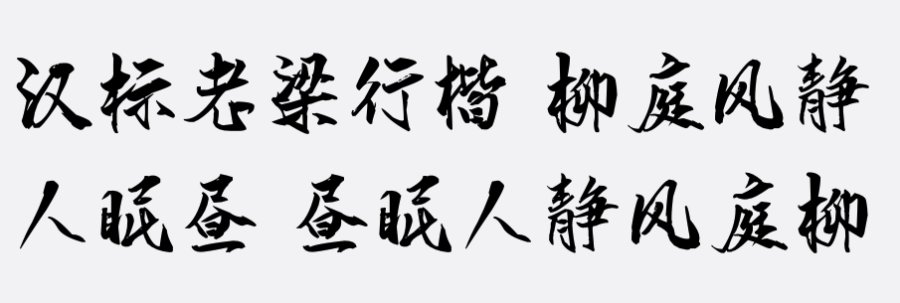
汉标智造国楷,书法气息浓厚,结字潇洒俊逸,运笔行云流水,气韵生动。适用于文艺类的书刊、品牌广告和产品包装设计。
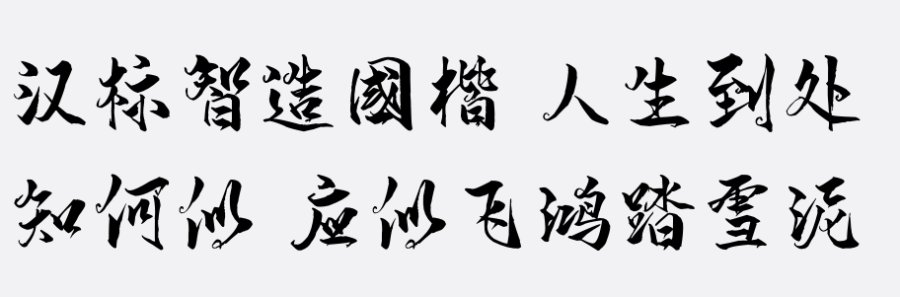
上首疾风书法体,字体风格锐利,钝点强力,夸张的笔锋增添了字体的活跃性,而且字体中粗细衔接,使字体显得生动。